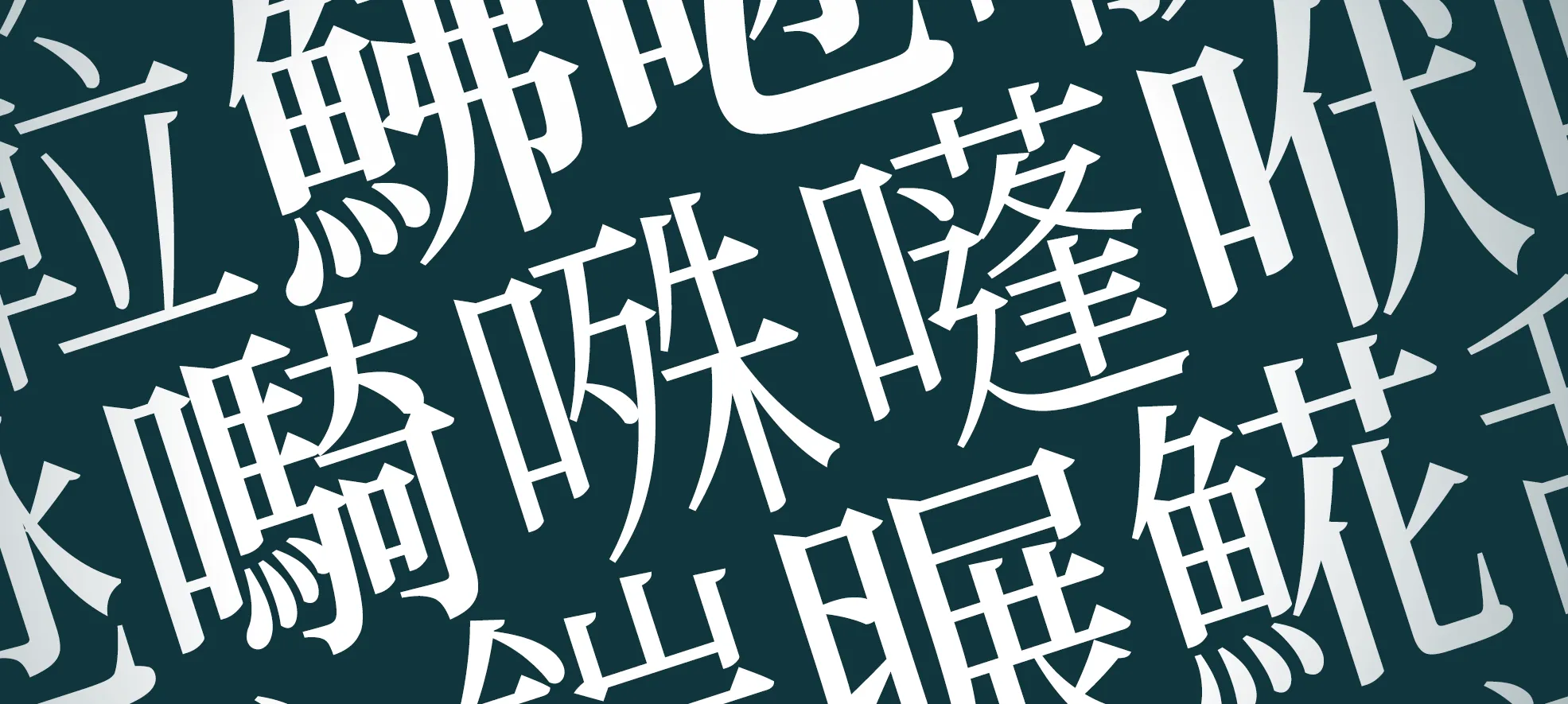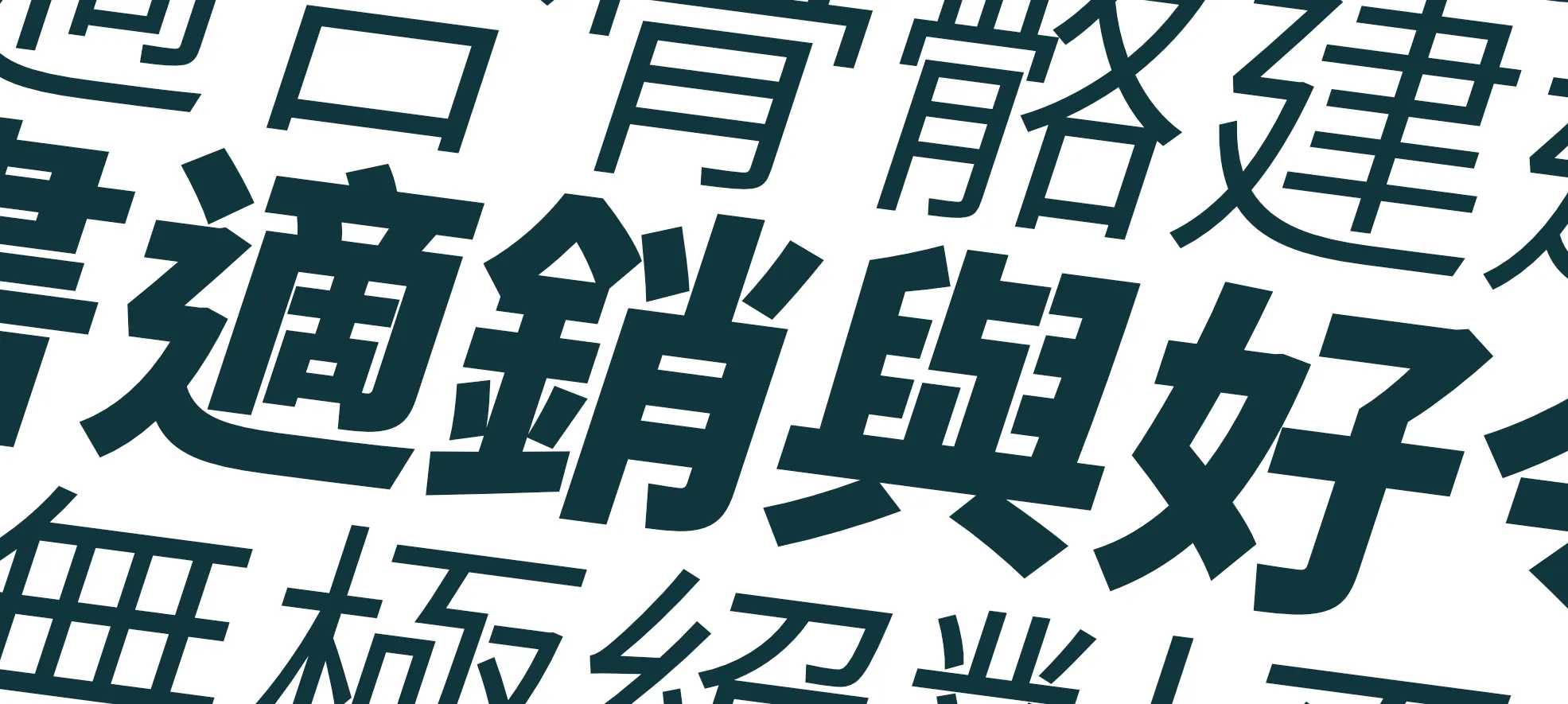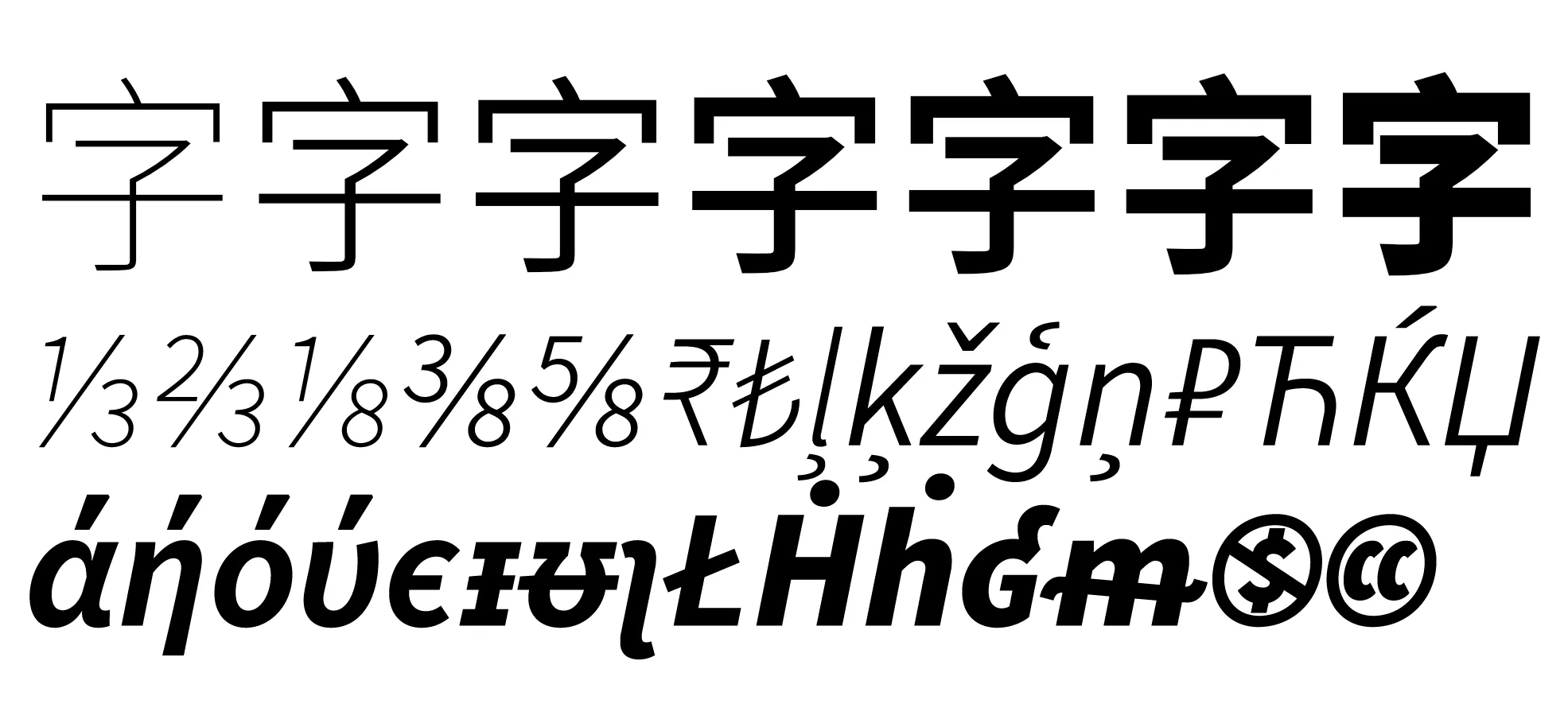
現代筆形,兼顧印刷體架構
「昭源黑體」以「思源黑體香港版」為基礎,參考繁體中文地區的商用字體作出修改,目標是提供一個正體中文標準、地區中立、採用現代筆形風格而兼顧標準字形和印刷體架構的開源字體方案。 (差異説明)
收字繁多,香港字支援充足
昭源字體完整保留思源字體的字碼支援,除了繁體中文會用到的 Big5 和 HKSCS 字集,其他如日本專用的和製漢字(例如「𩸽」、「峠」)亦不缺,日語假名、韓國諺文等也一應俱全。昭源字體率先支援 HKSCS 新增字元,包括 2021 年納入《香港增補字符集》補編的「𫬷」、「𭉝」和 2025 年通過增收的「㗩」。 (有關新增字元)
豐富字重,宋、黑體另有斜體、Text 家族分支
每款字體至少備有 8 款粗幼(粗細),還提供能精確控制字形粗幼的可變式字型 (Variable Font) 格式。昭源宋體和黑體更提供適用於內文印刷的 Text 家族分支和英數字元來自真正斜體而非由機械產生的 Italic 斜體配置。 (有關新增字重)